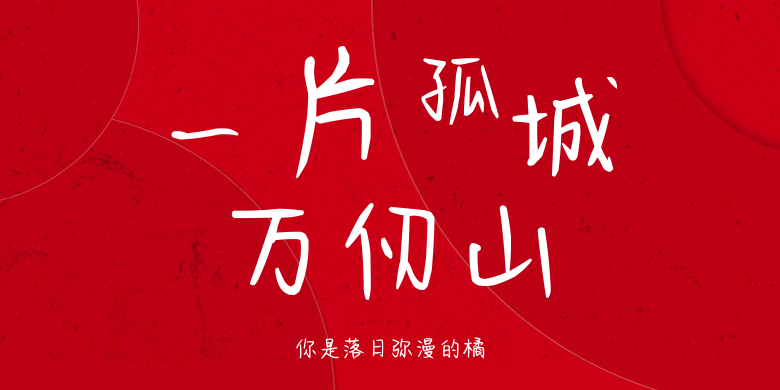
你是落日弥漫的橘
你是落日弥漫的橘,这款字体结构工整、笔画清晰,兼顾美观与易读性,适用于标题、正文、海报、包装、LOGO 等多种场景。字形优雅稳定,风格百搭耐看,适配日常排版与创意设计,让文字呈现更舒适、更具质感。你是落日弥漫的橘一笔一画,皆是细节,以均衡的比例、流畅的线条打造舒适视觉体验,字形端正大气,风格简约现代。无论是商业设计、品牌宣传还是日常排版,都能轻松驾驭,让文字更有格调与力量。你是落日弥漫的橘字体下载。